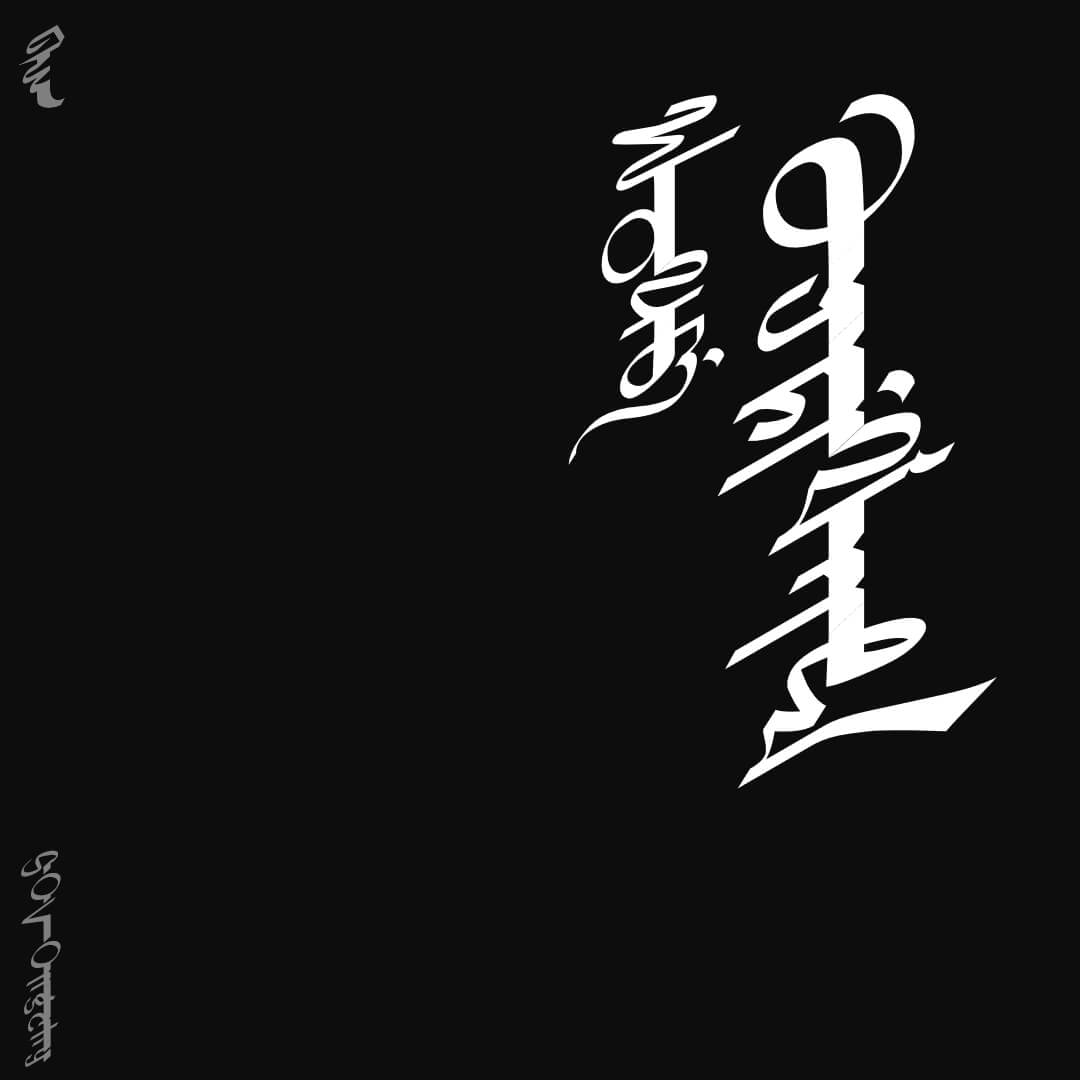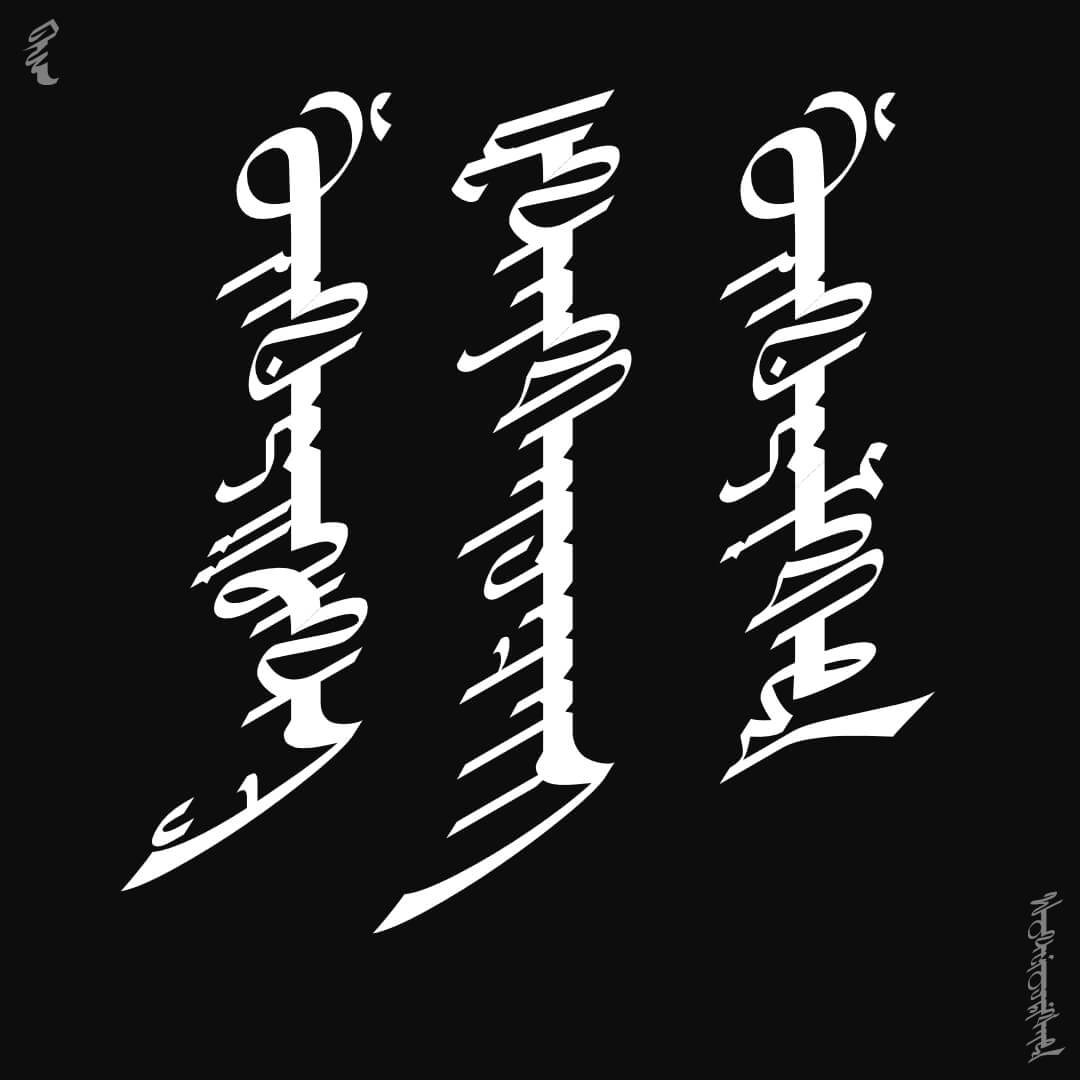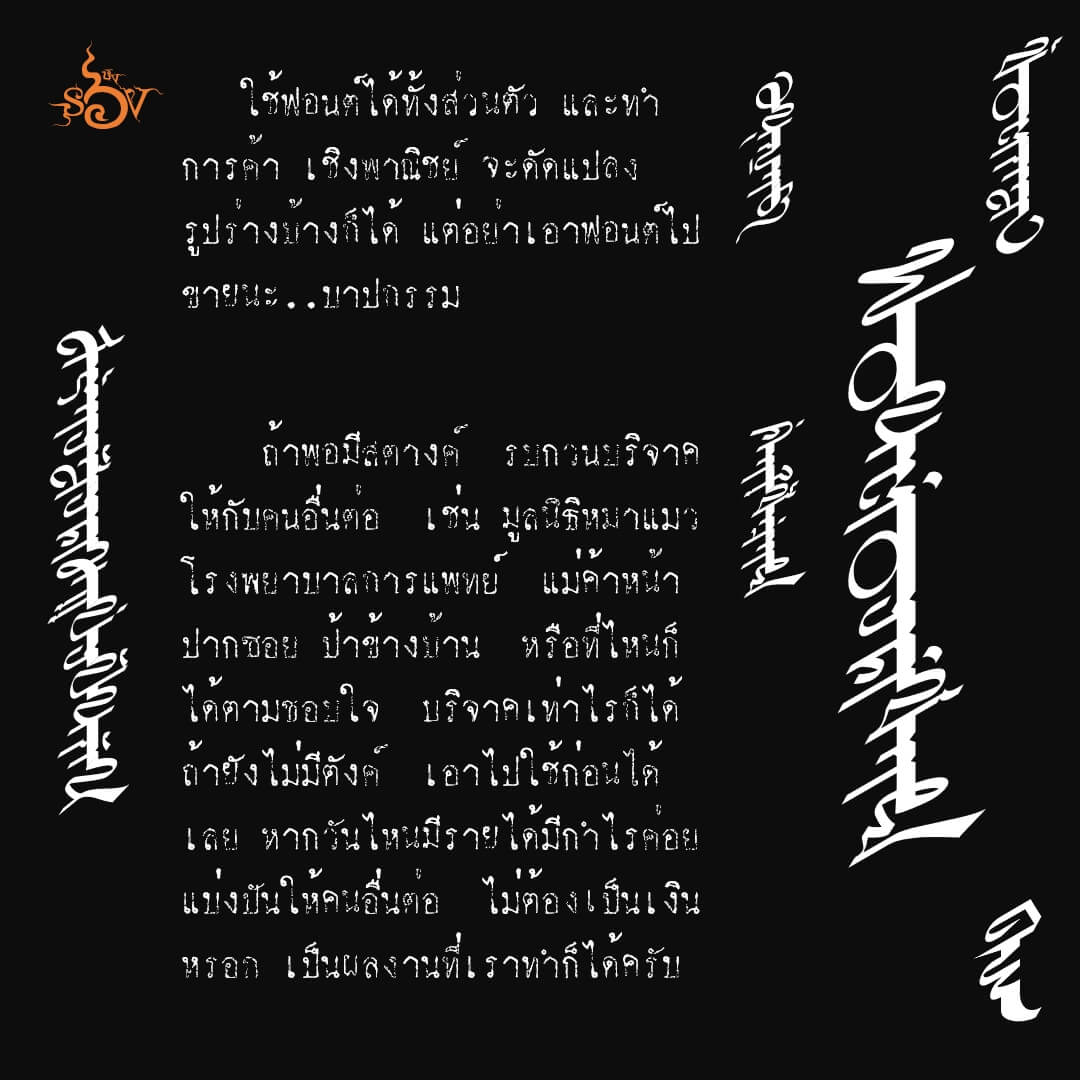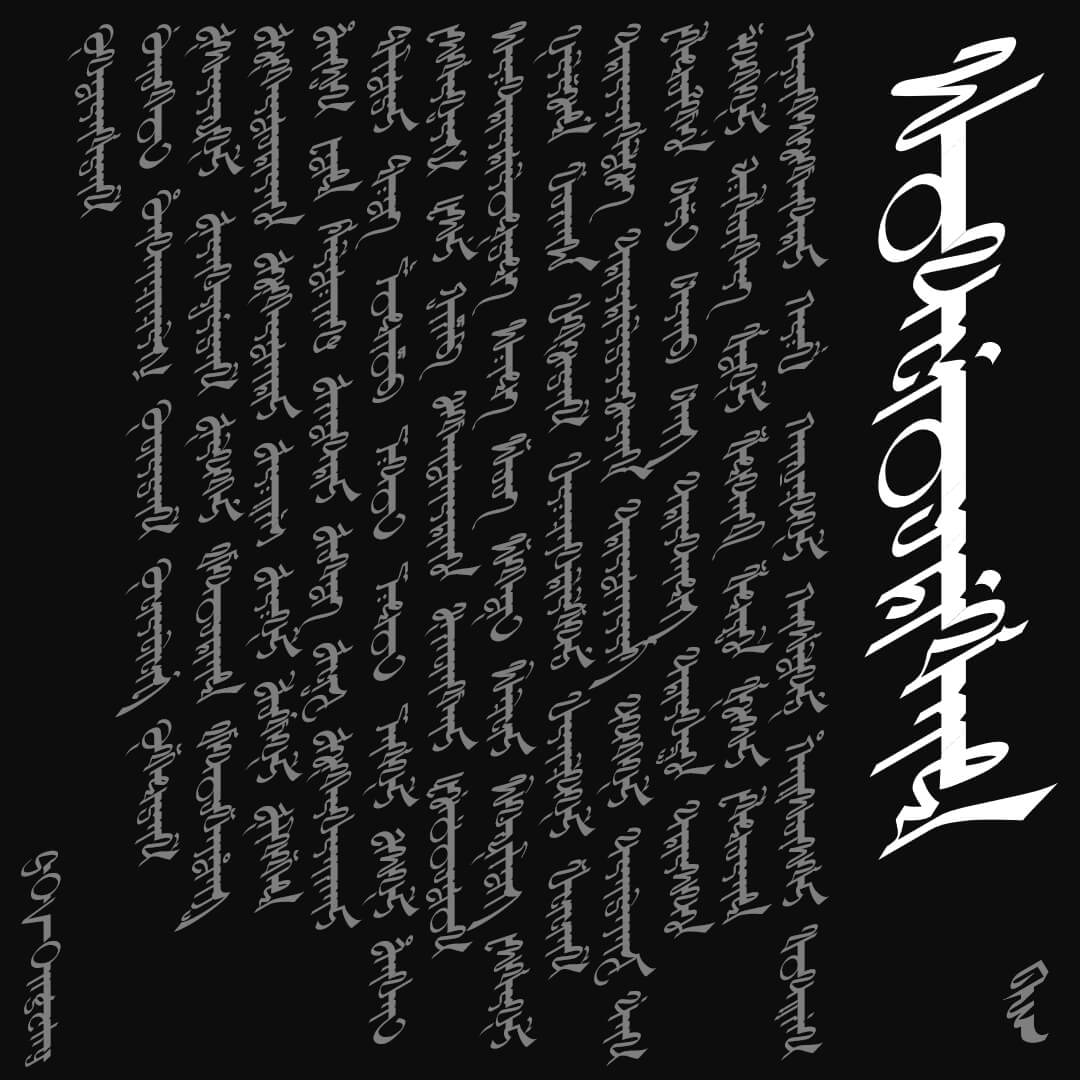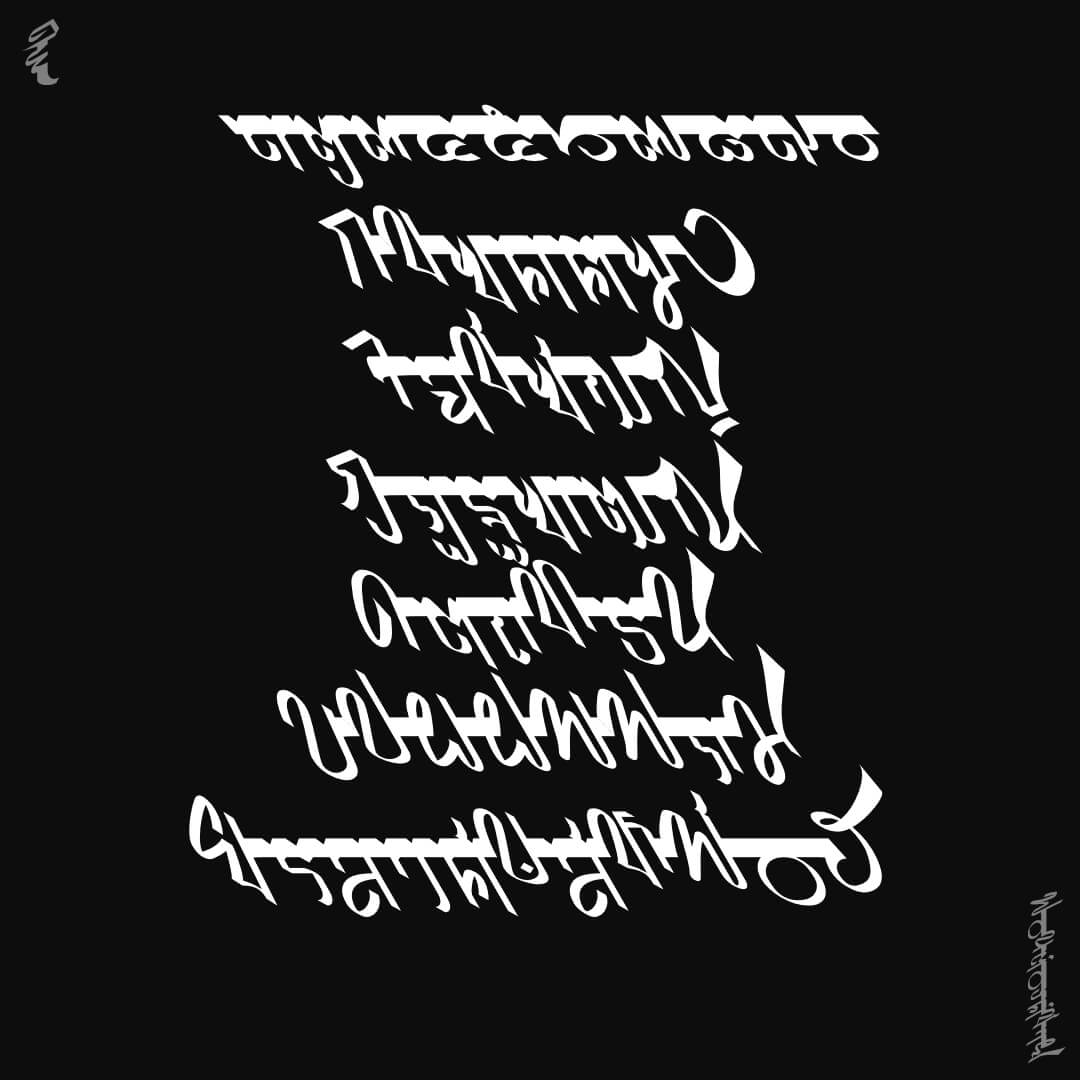
ฟอนต์องค์ชาย – “อ่านไม่ออกเหรอ? เอียงคอไปทางขวานิดนึง” ฟอนต์เชื่อมเส้นแนวตั้งจากบนลงล่าง ต้นทางจากอักษรแมนจู แต่ไปเรียนรู้จากอักษรมองโกล เอามาหาแนวทางสำหรับอักษรไทย
วิธีใช้งาน พิมพ์ปรกติ แล้วหมุน 90 องศา ตามเข็มนาฬิกา
เบื้องหลังการออกแบบ : ฟอนต์ องค์ชาย
องค์ชาย (SOV_Ongchy)